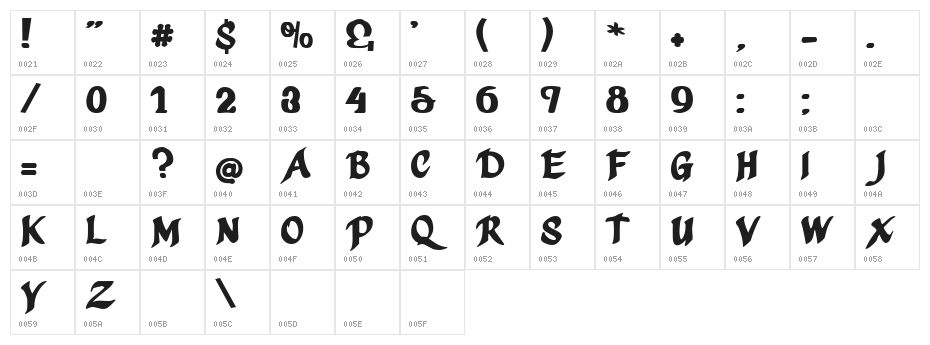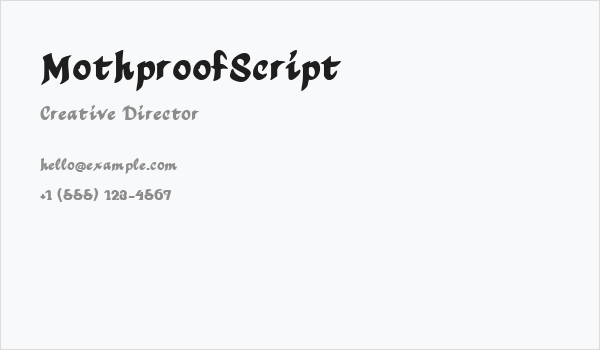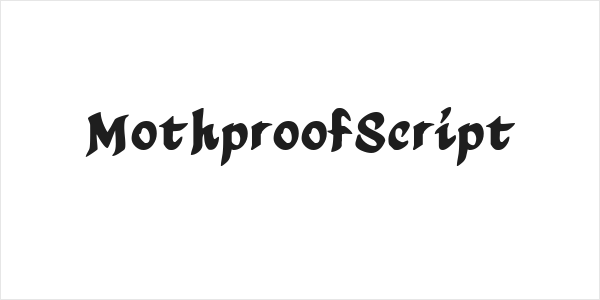
MothproofScript Font
✎ Calligraphic
| Anwendungsfall | Logos, Headlines, Posters |
| Vorgeschlagene Projekte | Ideal for branding, logo design, headlines, and posters where a bold, expressive style is desired. |